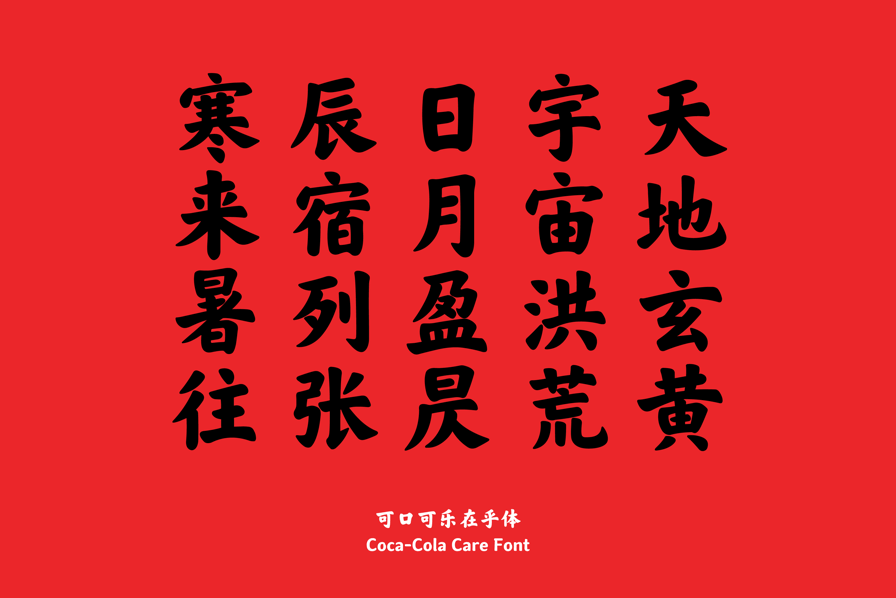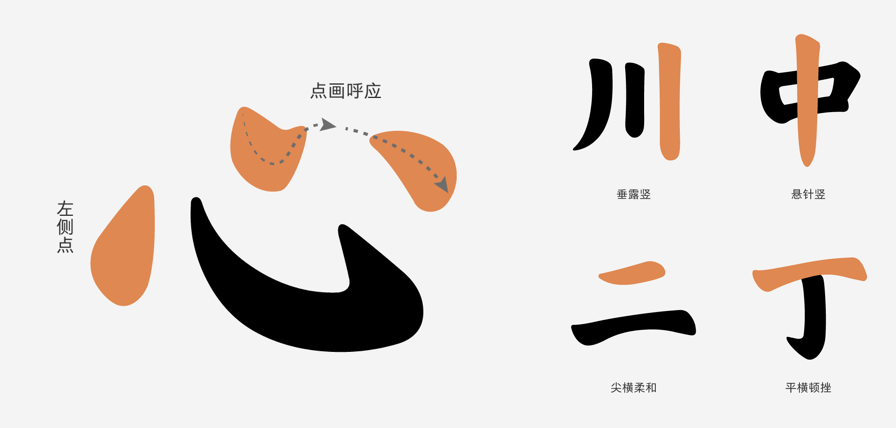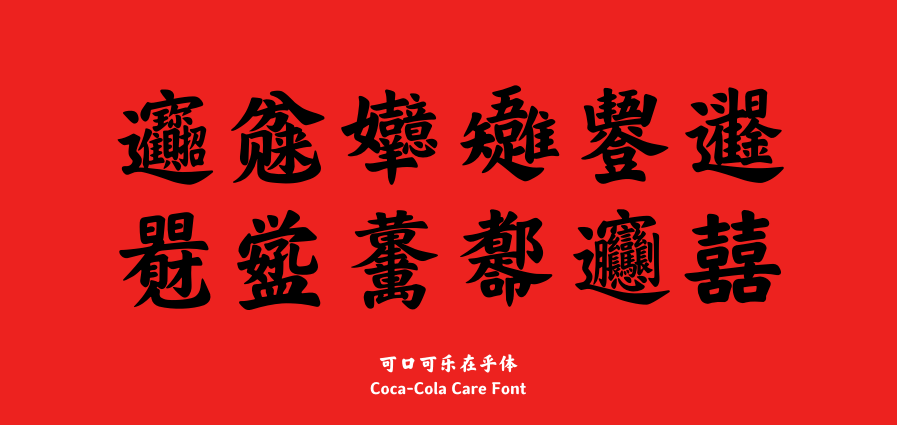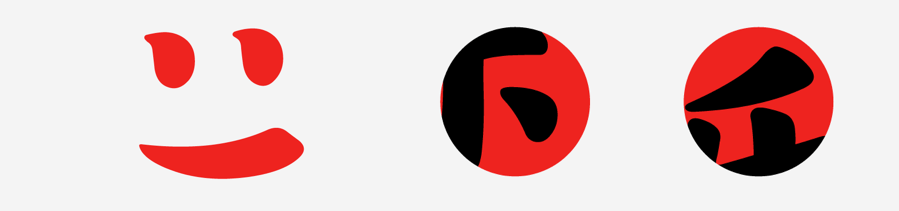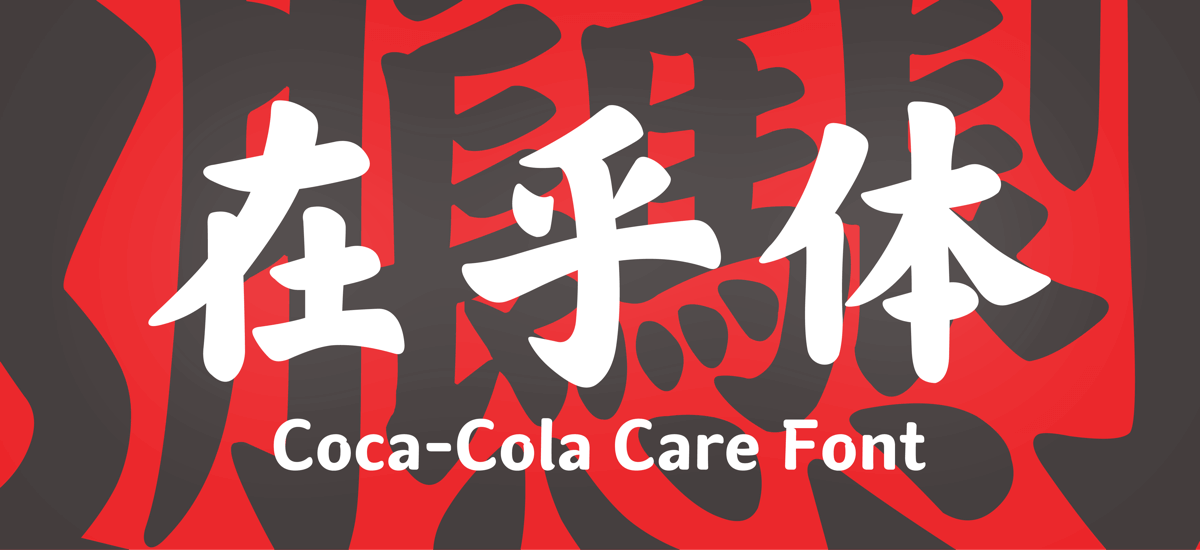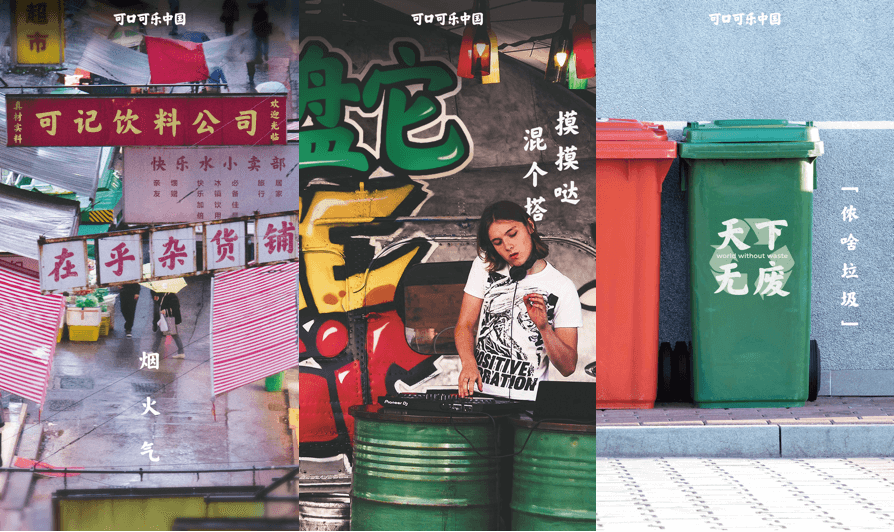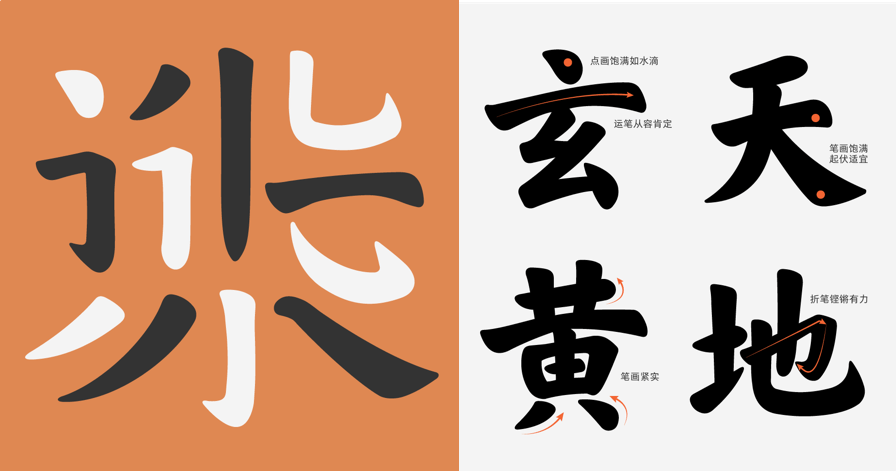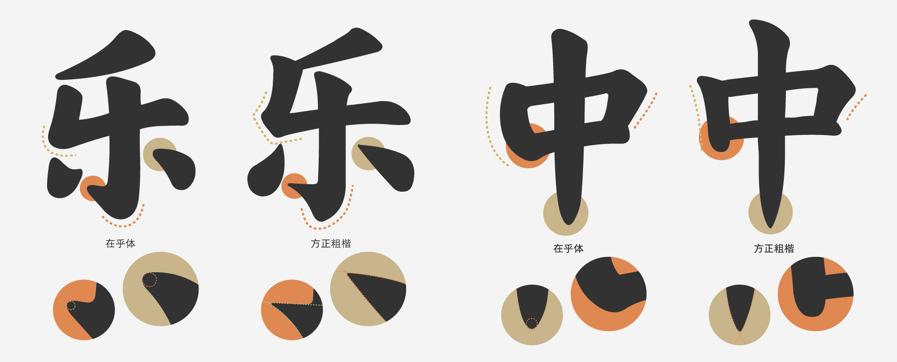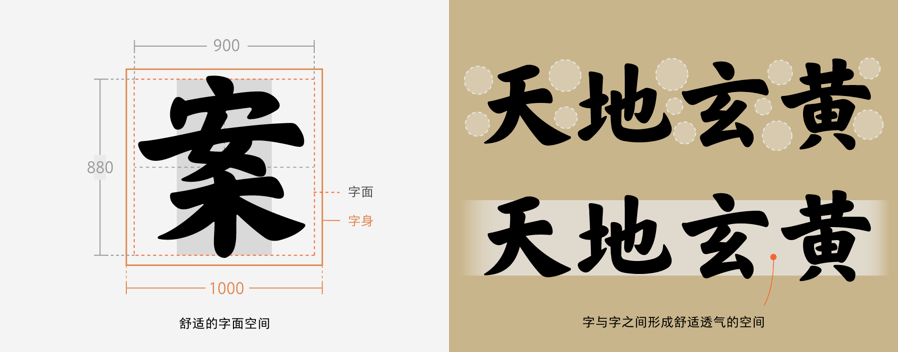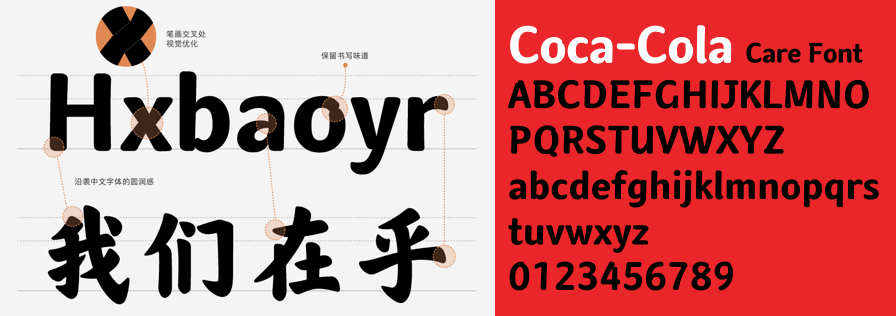
可口可乐在乎体
作为一款全新的品牌定制字体,“在乎体”从情怀出发,用具象的设计方法,借由每一笔一画,表达中国人对 “在乎”的理解和诠释——圆融、力量、担当、从容、进取,希望在数字化时代,为大家提供一种有人情味的字 体选择。用在乎体,写在乎的事,给在乎的人。
在中国,人们谈及书法总会提到“颜柳欧赵”,欧体的法度严谨、颜体的丰腴厚重、柳体的瘦劲硬朗、赵体的遒 媚秀逸,成为了千百年来学书者争相临摹的范本。作为中国文化的学习者,可口可乐在乎体在风格呈现上,体现 了对书法大家、古今贯通、东西融合的理解。
结字上以欧体为主、笔法上以颜体为主,将严谨、合理的结构与饱满、粗壮的笔画融合在一起,给人以浑厚、庄重、规矩的第一印象;与此同时,运笔从容肯定,笔画起伏适宜,也体现着对书法传统的致敬。
作为一家饮料公司,可口可乐中国对“水哲学”有着自己的理解,与中国文化对水的文化内涵的解读,有异曲同工之妙——从容又不失灵动;圆融与担当并重;上善若水,却不与万物争高下;既有 “水滴石穿”的坚韧,也有“海纳百川”的包容。
“在乎体”的设计也尝试融入水的形态与精神。点画好似水滴,饱满、灵动,横画起笔收笔、弯钩转折处的弧度,也兼顾圆润和力量感,运笔自然、流畅,有如行云流水一般。
“在乎体”不仅将水融于字,“在乎体”的笔画特征还彰显着书写意味,点画的形态,横画、竖画的笔法,都透着书写的韵律与活力。书写意味与水的形态相得益彰,赋予了“在乎体”厚而不重、流而不散、圆而不腻的精神面貌。
与此同时,在设计中,我们也一直思考如何将大家喜欢的“快乐水”畅爽感,融合进这款用“可口可乐”命名的字体。
冰凉气泡冲击喉咙、在口中绽放,满足得打个嗝,结结实实透一口气,这份自在,被吸纳进“在乎体”的设计中:笔画开张有度,字面留有充足空间,字间保持合适的距离,让排列变得通透,阅读更加轻松、舒服,有如自在呼吸。
“在乎体”西文的设计思路主要为配合中文的风格和气质而确定。字重较大,字形偏方并带有手写特征,笔形偏圆,带有倒角。在与中文风格匹配的同时,更体现年轻感和亲和力。中西文的搭配,也确保了“在乎体”在不同国家和地区的实用性。
“在乎体”是根据GB2312字符集设计制作的,但特别收录了GBK字符集中“凊”“鹍”等汉字,使用在乎体可以打出《千字文》的全文。
我们还为可口可乐在乎体特别设计制作了中华传统民俗文化中的“合体字”以及陕西特有的“biang”字,利用在乎体的Opentype特性,可以方便地调用这些特别设计的字符。中国民间常用的喜庆汉字“囍”(属GBK字符集)也有收录。
此外,可口可乐中国企业特别定制版字体中,还包含了主品牌标识:“在乎的笑脸”表情符号。来自于“在乎体”的中文笔画。
在乎体实际应用场景